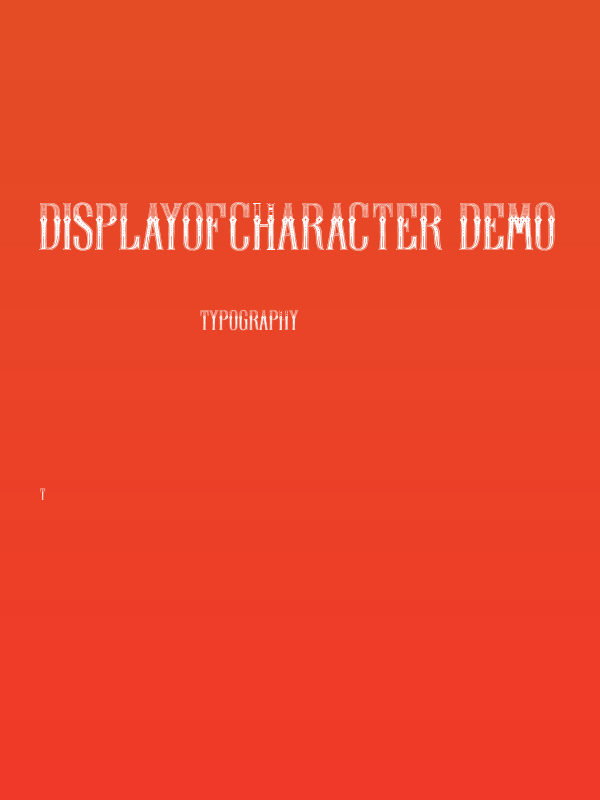
DisplayOfCharacter DEMO Font
✎ Art Deco
| Projetos propostos | Ideal for vintage-themed posters, invitations, branding for luxury products, or any project requiring a touch of elegance and sophistication. |